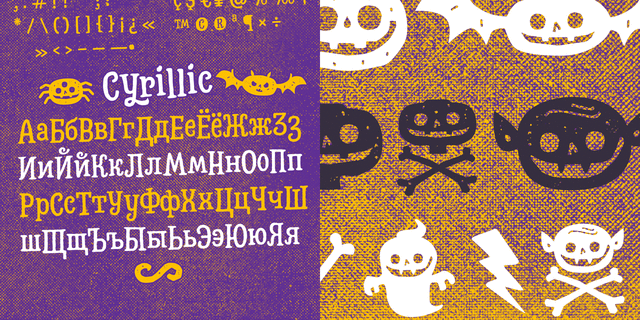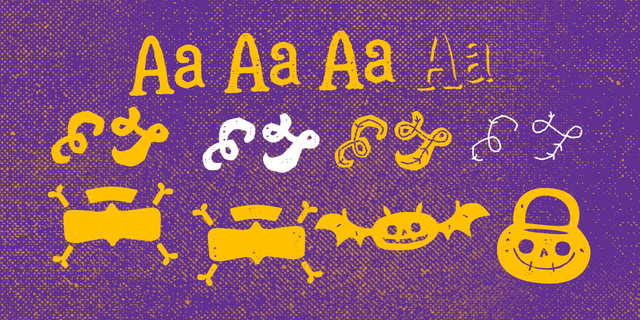
Это самая завершенная версия шрифта Безумного Шляпника. Он содержит 12 начертаний, которые поддерживают кириллицу, росчерки, альтернативные глифы, символы и орнаменты – все для создания развлекательной графики.
Этот сумасшедший шрифт создал Родриго Арая Салас в 2017 году.